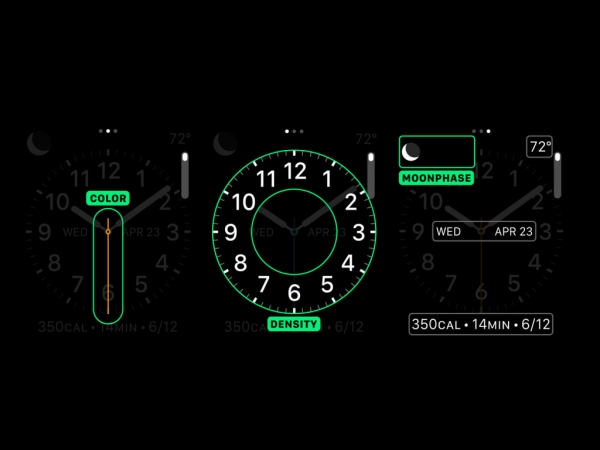
今年秋天,在蘋果經歷兩年的艱辛字體設計之後,定制字體 San Francisco 將逐步取代曾是世界上最受歡迎的字體 Helvetica Neue,成為 OS X El Capitan 作業系統與 iOS 9 作業系統的預設字體。
San Francisco 是蘋果總部 20 多年來設計的第一款蘋果產品專用字體。該字體不僅簡明、圓潤,而且字元間距較大。毫無疑問,該字體是為適應 Apple Watch 而專業設計的。但是,之前的 WWDC 會議上,在對全新作業系統和串流媒體音樂的大肆宣傳中,蘋果似乎悄悄的另有謀算:San Francisco 字體不僅專為 Apple Watch 的小螢幕設計,對於手機和電腦同樣適用。
當然,這個想法並不會向人們直接公開,種種跡象卻皆可表明這一猜想的真實性:贈送給大會出席者的外套上的白色「WWDC 2015」標誌均為 San Francisco 字體;展示在觀眾面前的巨大螢幕上畫面也顯示著 San Francisco 在新的作業系統中的應用。大螢幕上出現的字體是 San Francisco 字體還是 Helvetica Neue 字體,這兩種字體孰優孰劣,在 Twitter 上引發了字體迷們的熱切關注和熱烈討論。
精妙的設計為蘋果帶來了巨額的財富,因而不難想像它一定會對自己的字體設計藝術大加吹捧,但目前為止,它卻一直很低調,原因何在呢?
可能是蘋果想要挽回顏面。
「說到字體,蘋果是真的很落後。」著名的德國字體設計師 Erik Spiekermann 認為。2011 年,Google 推出了自訂字體 Roboto,幾年前 Spiekermann 也為 Mozilla 瀏覽器設計了 Fira Sans 字體。
由於蘋果在其他領域佔據著主導地位,所以如果設計的字體達不到一流水準,必會受到人們的各種批評,這對蘋果有點苛刻。Type Supply 公司的印刷工和程式師 Tal Leming 評論說,San Francisco 字體並不完美,數位的應用就有漏洞,比如數位 6 上半部分太封閉,在使用時就經常會出錯,顯示出來看著像 8。 當然,在他看來這些是可以忽視的,因為不能過於吹毛求疵。
蘋果在字體設計上曾經起過領頭作用,最為顯著的成就是在 80 年代委託設計師 Susan Kare 設計過字體,但這已是過去。在最近的幾年裡,蘋果的使用者介面都在使用現成的字體,毫無創新。從 2000 至 2014 年,蘋果 OS X 作業系統一直使用 Lucida Grande 字體。直到兩年前 iOS 7 發表,蘋果宣布將為新系統提供新字體,即 Helvetica Neue Light 字體。但這一舉動幾乎受到了全球設計師的抨擊。因為這種字體對解析度較低的手機小型螢幕來說,太淡太細。於是蘋果最終放棄使用該字體,取而代之的是 Helvetica Neue 字體。僅僅在兩年之後,蘋果再次宣布更新其系統的字體。
Helvetica 字體和 San Francisco 字體之間的差異,即使從專業眼光來看也並不明顯,但確實存在。San Francisco 比 Helvetica Neue 字體更粗、更簡單。根據德國字體標準,San Francisco 字體的間距相對較大,在相對較小的手機螢幕上閱讀會更容易。
無可置疑,為小螢幕設計字體頗具挑戰性。想想你有多少次是把大寫的 I 當成了小寫的 1。在一次採訪中,蘋果人機介面的負責人 Alan Dye 對如何最佳化字體,以適應 Apple Watch 的小螢幕做了解釋。他說,字體形狀變得更加方正,但是會帶有柔和的圓角;同時,字體非常緊縮,字型大小比一般字體的要高,小寫字母也更高,因而更好辨認。另外,字體設計非常靈活,螢幕大小變化時,字體也會跟著變化。
San Francisco 字體對於以設計為主導的公司也許不是一個大膽的選擇,但是,為適應小螢幕,字體的清晰度比字體的靈活性更重要。畢竟,字體設計不僅僅是使用者介面的一種要素,在一些以輸入為主的行動程式中,它就相當於一個使用者介面。正如著名的印刷商 Tobias Frere-Jones 闡釋的那樣,在人機互動中,從簡單操作(確定或取消)到個人資料等敏感資訊的處理,字體輸入都普遍存在。
這足以說明為什麼不應隨意切換字體。「看見字體改變,就好像回到家發現家裡的牆都變成了另一種顏色,令人心生不快,」 Alan Dye說道。「不幸的是,蘋果繼引進 Helvetica 字體不久後,又要改變介面字體。」但他對蘋果的這一做法持肯定態度。「Helvetica字體適用性確實不高,所以,我全力支持 San Francisco。」